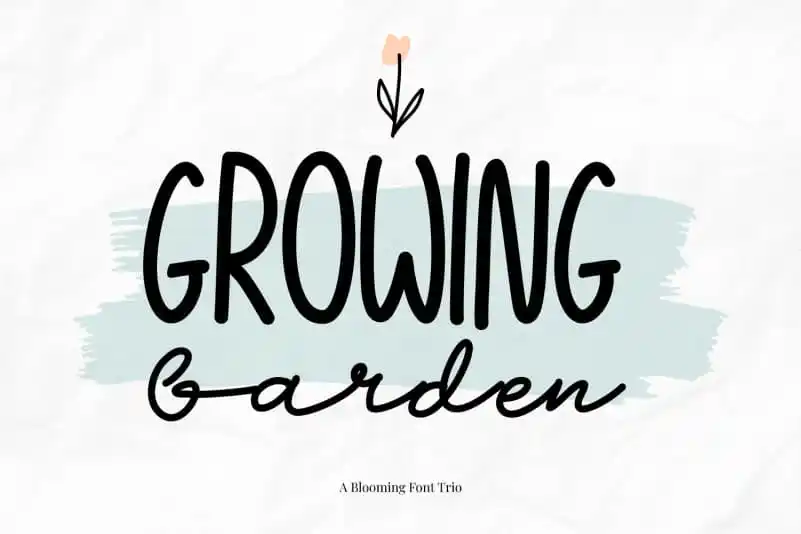
Growing Garden Font – Download Grátis
A Growing Garden Font é uma trinca de fontes minuciosamente escritas que transmitem elegância e naturalidade. Esta inovadora escolha para suas criações decorativas certamente despertará ideias criativas para projetos de decoração, como cartões de agradecimento, convites de casamento, cartazes de citações ou até mesmo logotipos. Com um toque delicado e único, essa fonte escrita à mão vai dar vida aos seus projetos digitais com uma aparência única e impecável. Seja em cartões de agradecimento sofisticados para suas amigas e familiares ou em um logo memorável para sua marca, Growing Garden Font oferece o acabamento perfeito. Essa fonte é ideal para tornar seus designs pessoais e únicos, fazendo você destacar no meio do monte de cartões digitais com uma aparência autêntica que chama atenção. É uma escolha perfeita para qualquer design que precise de um toque delicado e único, seja ele um convite elegante de casamento ou apenas uma citação inspiradora em seu site pessoal.
Designer: Heloyud